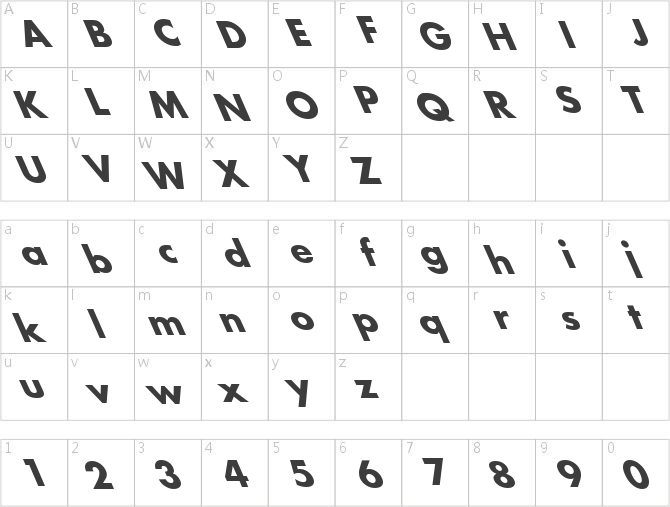
字體名稱: Fusion-
Fusion-Bold Lefty
Fusion-Bold Lefty字體字庫是一款讓人賞心悅目、百看不厭的英文字體,適合各類廣告和產(chǎn)品包裝設(shè)計(jì)應(yīng)用,字體大小0.03MB,格式為ttf字體,上傳用戶是woslxn,作者/版權(quán)方為未知